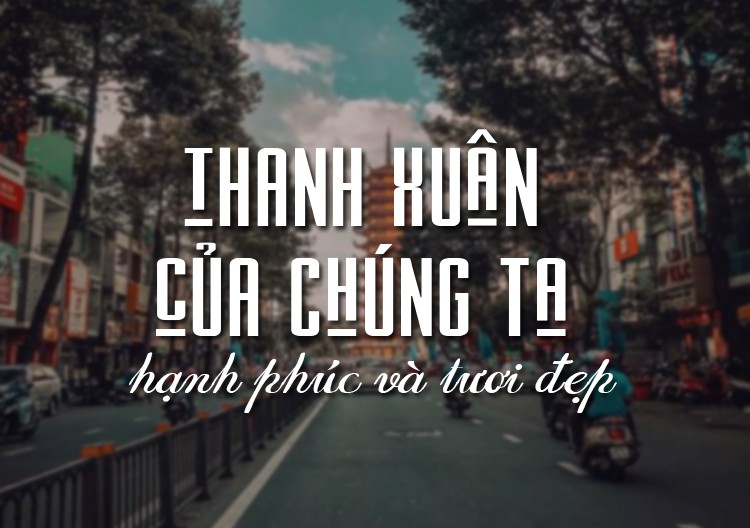
Giới thiệu về Font việt hoá MJ TheHustle
Trong thế giới đồ họa hiện đại, việc tìm kiếm một bộ Font Chữ vừa mang nét cá tính, vừa hỗ trợ đầy đủ tiếng Việt là điều vô cùng quan trọng. Font việt hoá MJ TheHustle là một trong những lựa chọn hàng đầu cho các nhà thiết kế muốn tạo điểm nhấn mạnh mẽ. Với các đường nét dứt khoát và phong cách đậm chất đô thị, bộ phông này mang lại nguồn năng lượng tích cực cho mọi sản phẩm sáng tạo.
Đặc điểm nổi bật của MJ TheHustle
Bộ phông này thuộc phong cách sans-serif nhưng được tinh chỉnh để mang lại cảm giác trẻ trung và hiện đại. Bản việt hóa đã được xử lý kỹ lưỡng, giúp các dấu tiếng Việt không bị lệch hay lỗi hiển thị, đảm bảo tính thẩm mỹ cao nhất trên mọi thiết bị.
Ứng dụng thực tế của Font việt hoá MJ TheHustle
Nhờ tính linh hoạt cao, Font việt hoá MJ TheHustle phù hợp cho nhiều mục đích khác nhau. Bạn có thể sử dụng nó để thiết kế bìa sách, làm tiêu đề cho bài thuyết trình hoặc tạo các hình ảnh truyền thông trên mạng xã hội.
Phù hợp cho giáo dục và học tập
Với các bạn học sinh và sinh viên, đây là công cụ đắc lực để trang trí bài tập lớn hoặc làm poster câu lạc bộ. Sự rõ ràng của các ký tự giúp người xem dễ dàng tiếp nhận thông tin mà vẫn cảm thấy sự mới mẻ, chuyên nghiệp trong cách trình bày nội dung bài học.